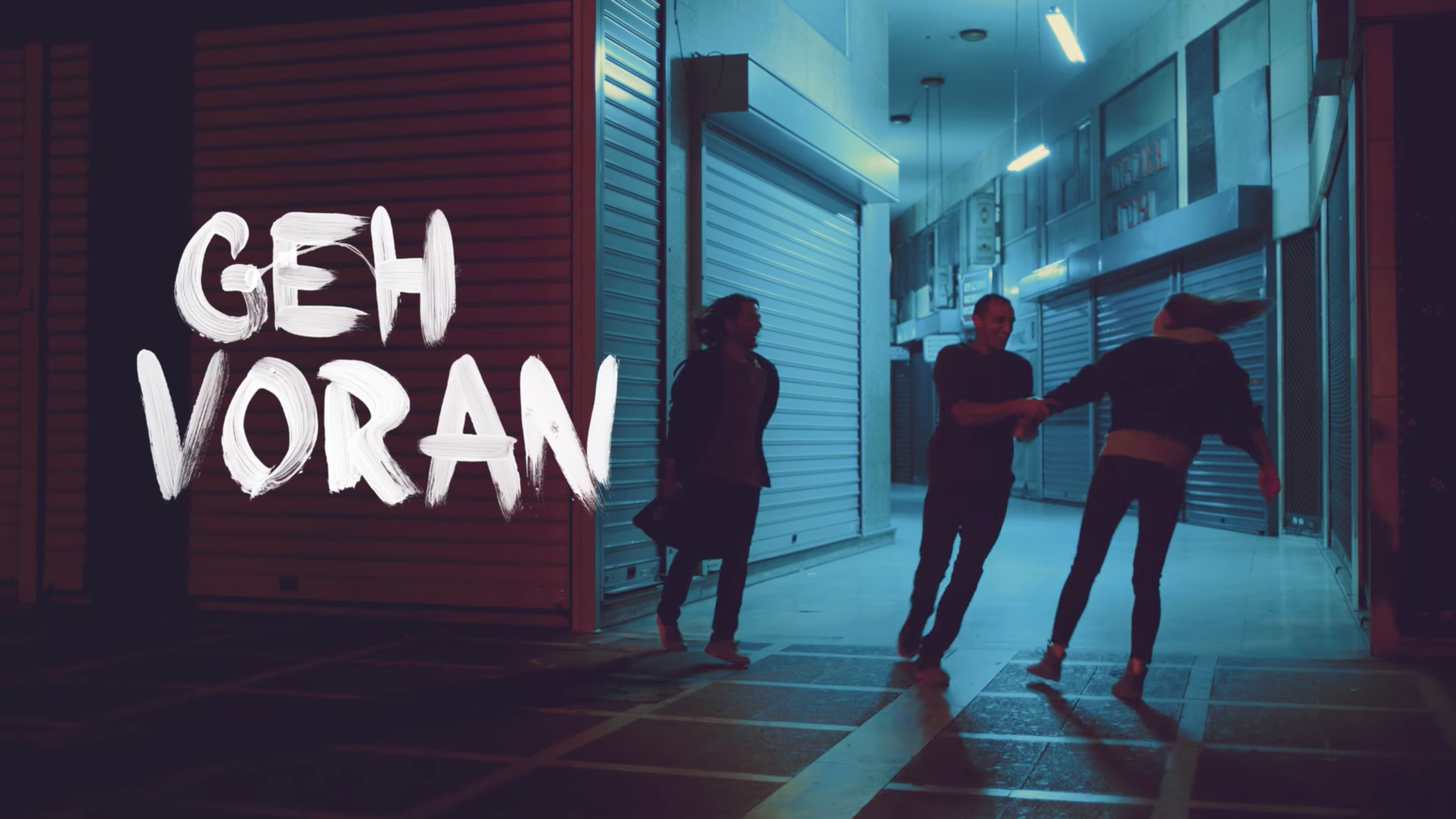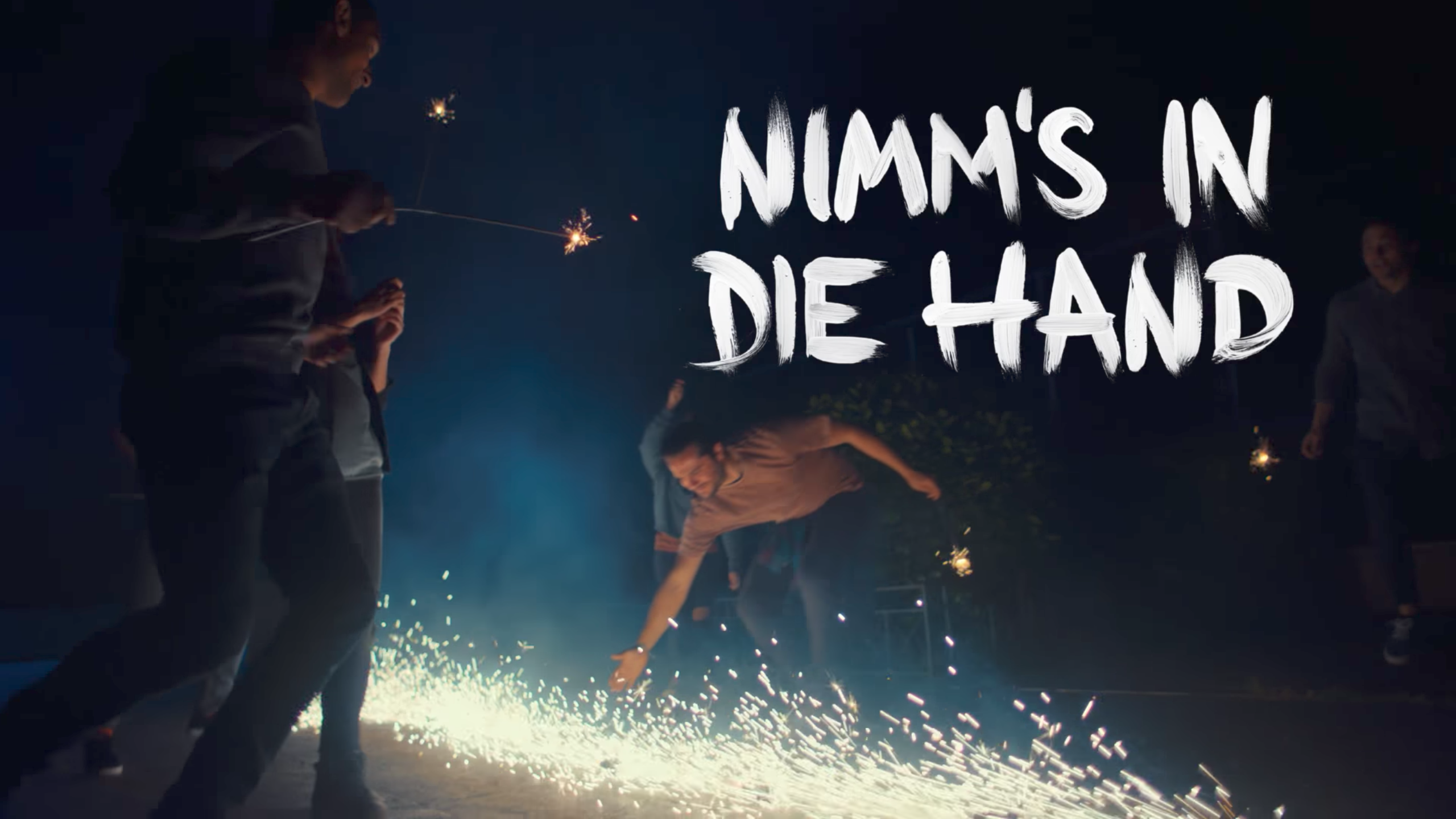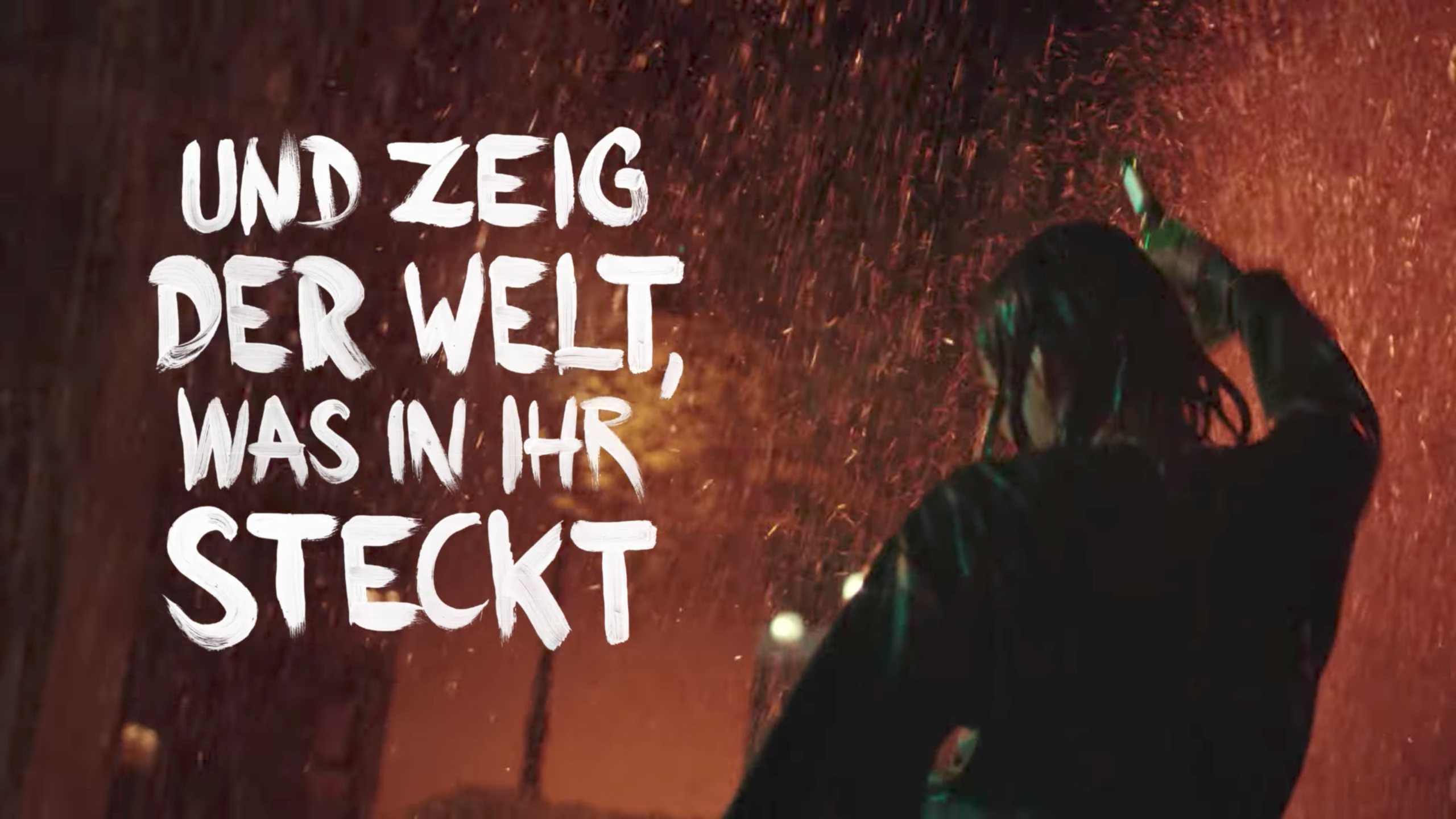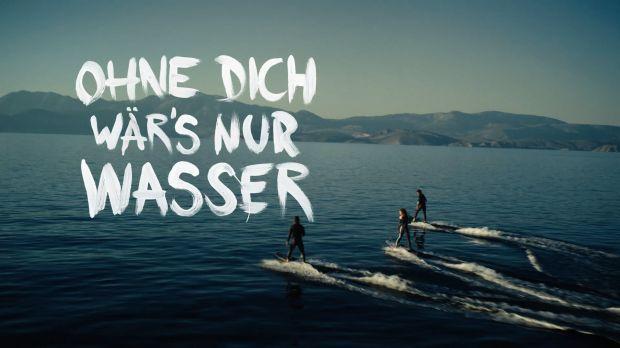
Wie heißt diese Schrift (Wasserfarbe,Pinsel, Becks)
kennt ihr den Namen dieser oder einer vergleichbaren Schrift?
So viele gleiche Buchstaben mit so vielen unterschiedlichen Formen gibt es in keiner Satzschrift.
Das S in Wär's und das erste in Wasser sind schon mal identisch.
und hier hab ich von jedem Buchstaben 9 Vesionen:
Du hast Recht, es sind pro Buchstabe nur zwei Formen.
Das S in Wär's und das erste in Wasser sind schon mal identisch.
und hier hab ich von jedem Buchstaben 9 Vesionen:
Danke schon mal - dennoch ist noch nicht klar, wie der Name der Schriftart ist... hmm...
Das wird so sein, weil die üblichen Schrift-Suchmaschinen an solchen Schriften scheitern.
Grund: ich habe von einem Buchstaben mehrere Formen, die über OpenType Funktionen getauscht werden, also weiß ich als Nutzer oft nicht, welches ist die codierte Grundform, und welches sind uncodierte Spezialformen, die durch die interne Logik in der Schrift die Standardform ersetzen.
Die Suchmaschinen können aber nur einen Bildvergleich zwischen den Standardbuchstaben anstellen. Wenn ich also ein Bild mit Schrift übergebe. muss das Bild intern in Sub-Bilder mit einzelnen Buchstaben zerlegt werden (und dazu natürlich auch zerlegbar sein. Diese Buchstaben werden per OCR - und der Hilfe des Einstellers dem dargestellten Buchstaben zugeordnet, und dann wird eben z.B. das B mit allen B in der Datenbank verglichen, und das für alle anderen im Suchbild vorhandenen Buchstaben auch. Habe ich im Suchbild aber 2 verschiedene B, dann wird eines davon garantiert nicht zum hinterlegten B passen, und die Wahrscheinlichkeit der Zuordnung des Bildes zu einer Schrift sinkt deutlich, habe ich aber z.B. einen anderen Buchstaben, und davon nur eine getauschte Form, also einen nicht unicode-codierten Buchstaben der Schrift, findet ihn das System überhaupt nicht in den hinterlegten Mustern, und das Suchbild kann noch weniger einer Schrift zugeordnet werden.
Dazu kommt, dass die Schrift im neuen Beck’s-Markenauftritt verwendet wird. Hier liegt die berechtigte Vermutung nahe, dass die Buchstaben exklusiv für Beck’s gestaltet wurden und deshalb in keiner verfügbaren Schrift zu finden sind.
Und zudem in den Buchstaben einfach zu feine Halbton-Abstufungen drin sind, kann es auch kaum eine Vektor-Outlineschrift sein, sondern möglicherweise ein Sortiment mit 48 relativ hoch aufgelösten graustufen Pixelbildern.